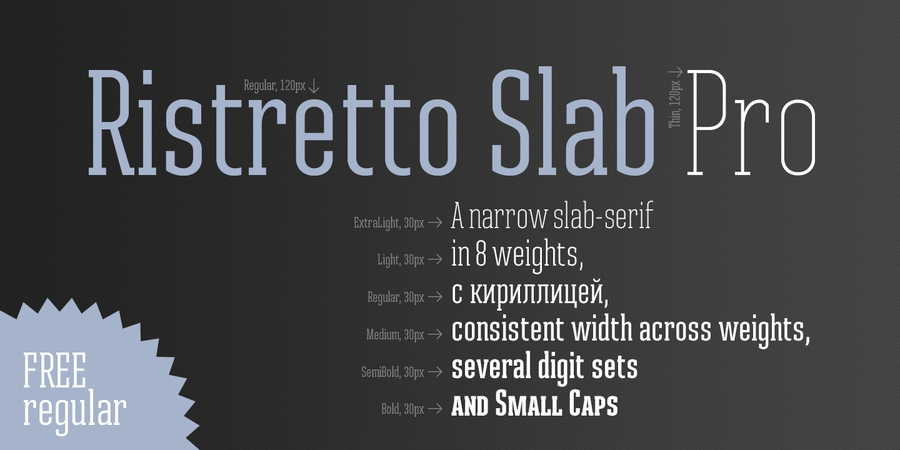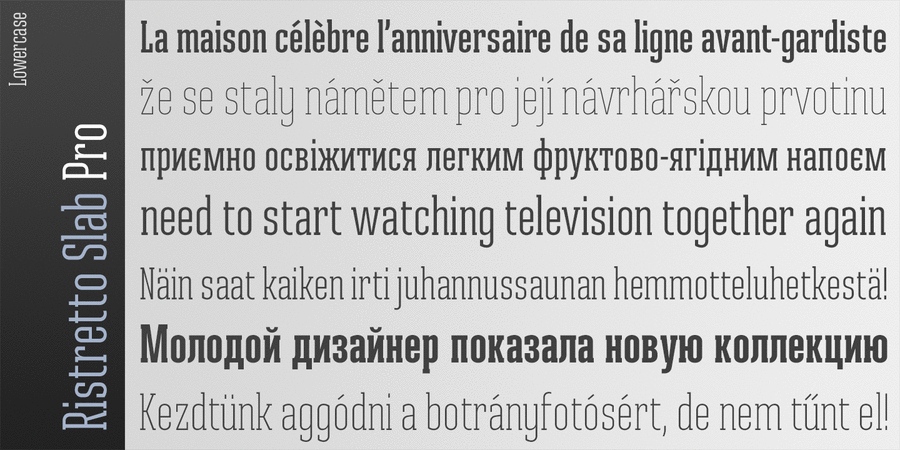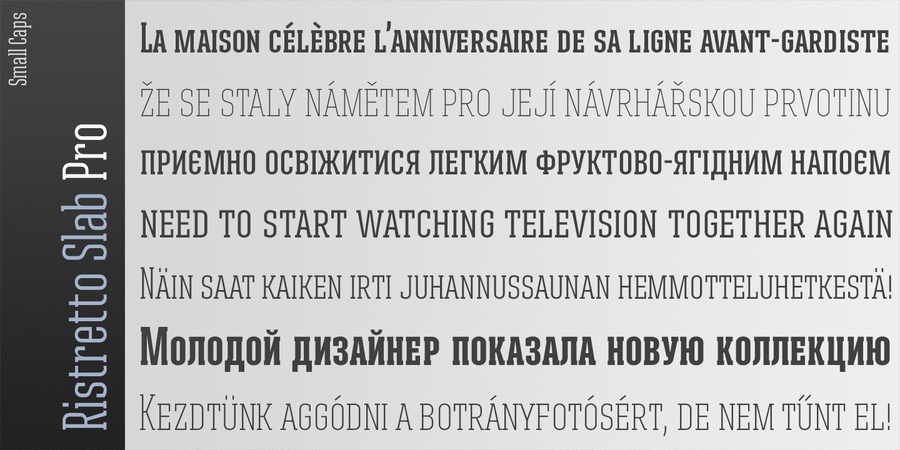
Опис гарнітури Ristretto Slab Pro – це брусковий компаньйон шрифту Ristretto Pro. Це надвузький акцидентний шрифт з асиметричными брусковыми зарубками, доступний у 8 насиченостях. Гарнітура підтримує безліч мов, 6 наборів цифр та капітель.
Шрифт Ristretto Slab Pro розробив і випустив Андрій Константинов у студії Mint Type у 2013 році.
Особливості сімейства шрифтів Ristretto Slab ProХіт десятиліття:
Асоціації з сімейством шрифтів Ristretto Slab ProОсобистість і характер гарнітури:
тонкий, стрункий, худий, рівний, статичний, високий, міський, вузький, технічний, якісний, точний, чіткий, крихкий, прозорий, дротяний, серйозний, стиснений, дорослий, стійкий, стабільний, твердий, гучний, впевнений, помітний, амбітний, важливий, мотивуючий, переконливий, міцний, сильний, тісний, техногенний, гострий, індустріальний, мужній, значний, прямокутний, надійний, суворий, яскравий, активний, крутий, грубий, різкий, робочий, важкий, залізний, сталевий, чорний, потужний, авторитетний, наполегливий, військовий, армійський, жорсткий, брутальний
Місто, дієта, кафе, хмарочос, новини, політика, будівництво, нерухомість, завод, промисловість, влада, техніка, інструмент, будматеріали, верстат, індустрія, енергетика, джинси, ремонт, охорона, захист, блокбастер, Футбол, робочий, Локдаун, нафта, металургія, поліція, екскаватор, війна, танк, зброя, сталевар, регбі, бойовик, армія Гарнітура асоціюється з віком: